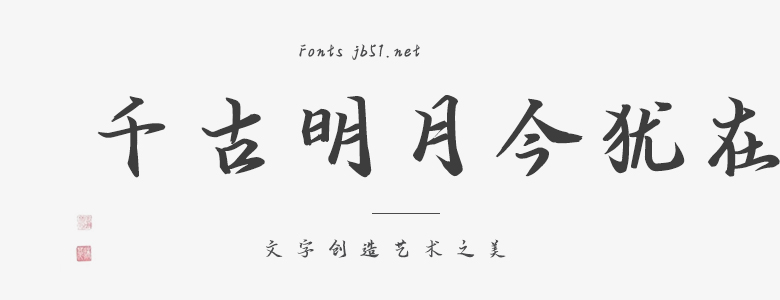
千古明月今猶在是一款獨特且富有文化內涵的字體設計。它的靈感源于中國古代書法,融合了傳統(tǒng)與現(xiàn)代的設計元素,呈現(xiàn)出一種極富藝術感的字體風格。 字體設計方面,千古明月今猶在采用了優(yōu)雅的曲線和流暢的線條,賦予了字體濃厚的東方韻味。字形舒展、婉轉,如同古代畫卷般緩緩展開,給人以無盡的遐想。同時,字體筆畫的設計也頗具匠心,運用了豐富的筆觸和層疊效果,表現(xiàn)出書法的韻律感和動態(tài)美。 在字體排版方面,千古明月今猶在強調和諧與平衡。無論是單個字體的排列,還是段落文本的布局,都追求整體的美感和協(xié)調性。通過巧妙的字距調整和重心控制,使字體在保持傳統(tǒng)書法韻味的同時,也適用于現(xiàn)代設計的審美需求。 千古明月今猶在不僅在視覺上獨具一格,還蘊含著深厚的文化內涵。字體設計的命名源于古詩中“千古明月今猶在,多少繁華付流水”的詩句,寓意著歷史的永恒與變遷。這款字體不僅體現(xiàn)了中國傳統(tǒng)文化的美學追求,同時也展示了現(xiàn)代設計的美學理念,是傳統(tǒng)與現(xiàn)代、文化與藝術的完美結合。 總的來說,千古明月今猶在是一款富有詩意和文化內涵的字體設計。它融合了傳統(tǒng)書法的精髓和現(xiàn)代設計元素,為設計師提供了一種獨特且富有藝術感的視覺表達方式。無論是應用于書籍、報紙、雜志等印刷品,還是數(shù)字屏幕、廣告牌等顯示設備,千古明月今猶在都能展現(xiàn)出其獨特的魅力。